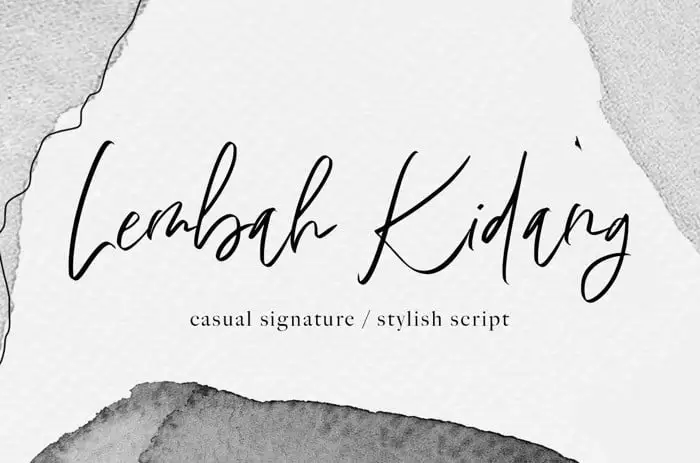
Lembah Kidang Handwritten Font – Download Grátis
Descubra uma nova opção para seus projetos digitais com a Lembah Kidang Handwritten Font. Esta elegante fonte escrita à mão foi criada pela Agniardi e está disponível na categoria de Fonts Script do nosso site. Ideal para designers profissionais, essa font oferece inúmeras possibilidades para criar designs distintivos. Utilize-a para criar logotipos de assinatura, cartões de convite, cartões de visita, mensagens inspiradoras, materiais de publicidade, cabeçalhos de blog, design para casamentos e embalagens, bem como arte impressa personalizada. A Lembah Kidang Handwritten é uma fonte de escrita à mão perfeita para aqueles que buscam adicionar um toque único a seus projetos. Seja para seu próximo projeto, este é o elemento perfeito para fazer sua marca mais imponente e única.